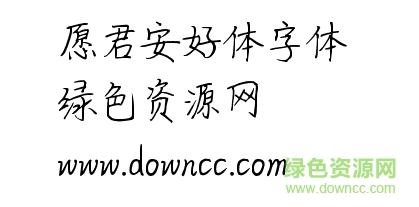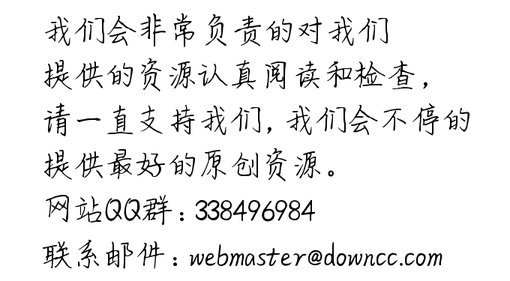
愿君安好體是一款給人淡然舒暢的手寫書法字體體驗(yàn),有著隸書和楷書的風(fēng)范,讓字跡清秀端正,拜托了中規(guī)中矩的宋體模板,更顯得張揚(yáng)而內(nèi)斂!
“愿君安好,吾愿足矣。”——愿君安好體。
愿君安好體字體字跡清新而亮麗,中文飄逸、英文活潑,無論用于平面設(shè)計(jì)、海報(bào)設(shè)計(jì)還是排版印刷都有著獨(dú)特的美感,大家可以來本站試試!